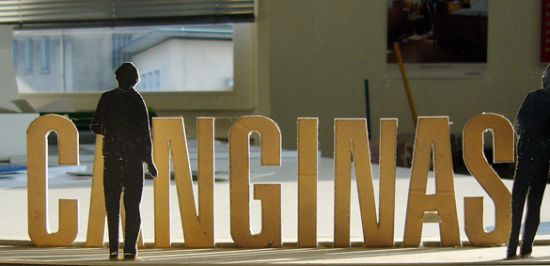
Buchstaben zum Aufstellen
ich benötige - für eine Messe - Buchstaben zum Aufstellen, etwa in Thekenhöhe von 1,20 Meter. Das Material ist erst einmal egal, beleuchtet wäre schön.
Ich war schon bei Leuchtbuchstaben-Herstellern und kenne diese Site:
Hat jemand noch eine andere Idee?
hallo oliver, sowas macht dir jeder größere schilderhersteller um die ecke.
es sei denn du suchst was spezielles. ansonsten ist das aber kein problem,
plexiglas, schrift ausuchen, zurechtschneiden und zusammenmontieren, fertig.
Naja, daß das Material egal ist - das sag mal den Herren von der Messe. Nachdem Du alle Auflagen hinsichtlich Feuerfestigkeit und Brandschutz erfüllt hast, bleibt am Ende nicht mehr viel übrig, aus dem Du was bauen kannst. Die Nummer mit set26 ist doch so schlecht nicht. Habe ich auf der Möbelmesse in Köln gesehen, machen was her und vielleicht gibt´s in deiner Stadt (oder Umgebung) ja ein Möbelgeschäft, bei dem Du die leihen kannst. Oder bei set26 direkt.
Was ist denn mit Blöcken aus PUR oder Polystyrol? Leicht zu bearbeiten und lassen daher viel Gestaltungsmöglichkeiten offen. So 'ne ganze Theke aus der Klingspor - den Schildermacher möchte ich sehen, der das zu einem vertretbaren Preis macht. ;-)
Die Nummer mit set26 ist doch so schlecht nicht.
Richtig. Das Logo bei meinem Kunden ist aber in der fetten Helvetica gesetzt … Vor allem das S fällt bei set26 aus dem Rahmen ...
Wie wär's mit Eisen? Habe vor Jahren mal sowas als "Bautafel" mit Prospekt-Dispenser (unten am A-Balken) geplant. Die Buchstaben waren so gegen 1,5 m hoch und sollten einfach vor sich hin rosten. Kostenvoranschlag des Metallbauers (Buchstaben mit Laser aus Eisenplatten geschnitten) so ca. CHF 2500 (so gegen 1700 Euro vielleicht?)
Aber eben, das ist länger her, zu Zeiten, als sich China noch im Fahrradtempo fortbewegte ;-)
Ich würde dem Kunden die Buchstabenschränke auf´s Auge drücken und ein Re-Design für seine Hausschrift/Logo etc. direkt dazu. ;-)
Gute Idee, leider nicht möglich :wink: ! Zumal mir diese Buchstaben auch nicht gefallen ...
Tja dann: Entwurf machen, MDF kaufen, viel Geld bezahlen, zuschneiden, in Finger schneiden, fluchen, wieder neue Platten kaufen, zusammenbauen, ... also mir würden diese Buchstaben von set26 echt gut gefallen - auch wenn sie mir nicht gefallen. ;-)
Im Ernst und wie wär´s damit: Buchstaben aus Metall wie wie von Norbert gesagt lasern, aber von jedem Buchstaben zwei Exemplare, mit Abstandshaltern auf gewünschte Tiefe gegeneinander montieren und die dann entstandene Tiefe mit Acryl verkleiden. Das ganze dann noch von innen beleuchten.
Gleiches geht natürlich auch komplett aus Acryl, aber das wird bei den großen Flächen der Fronten so wabbelig und ist wegen der Opazität des Acryls sehr kompliziert mit versteckten Innenbefestigungen.